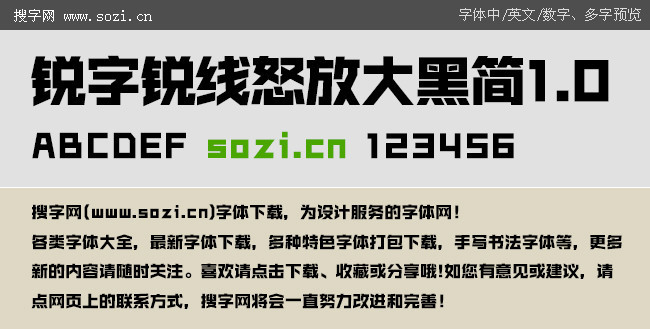
銳字銳線(xiàn)怒放大黑簡(jiǎn)1.0
搜字網(wǎng)提供一款非常藝術(shù)的銳字銳線(xiàn)怒放大黑簡(jiǎn)1.0下載,銳字銳線(xiàn)怒放黑簡(jiǎn)是一款銳字工房出品的藝術(shù)字體,該字體極具藝術(shù)感,簡(jiǎn)潔大方,適用于包裝印刷、廣告設(shè)計(jì)、平面設(shè)計(jì)、書(shū)籍報(bào)紙等領(lǐng)域。